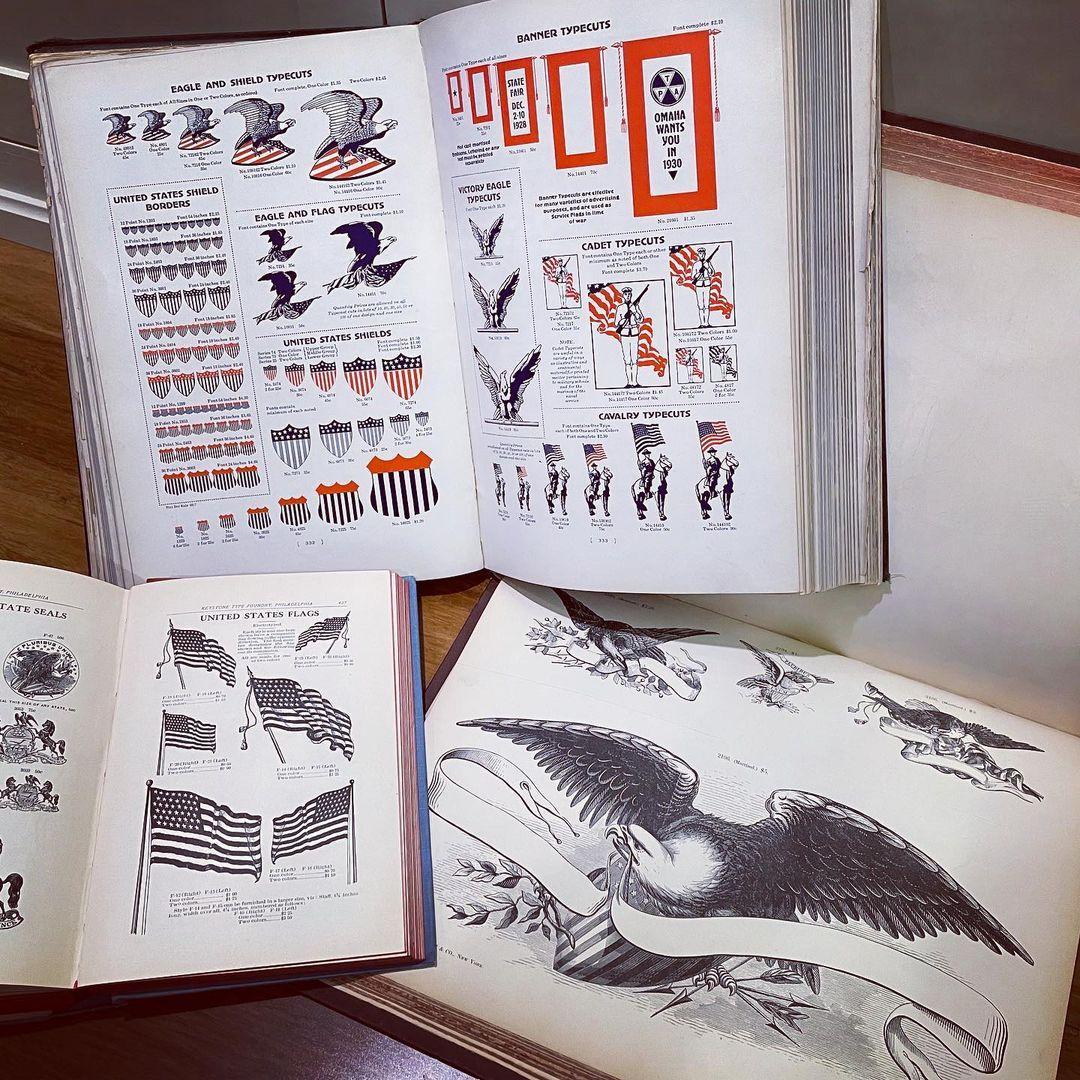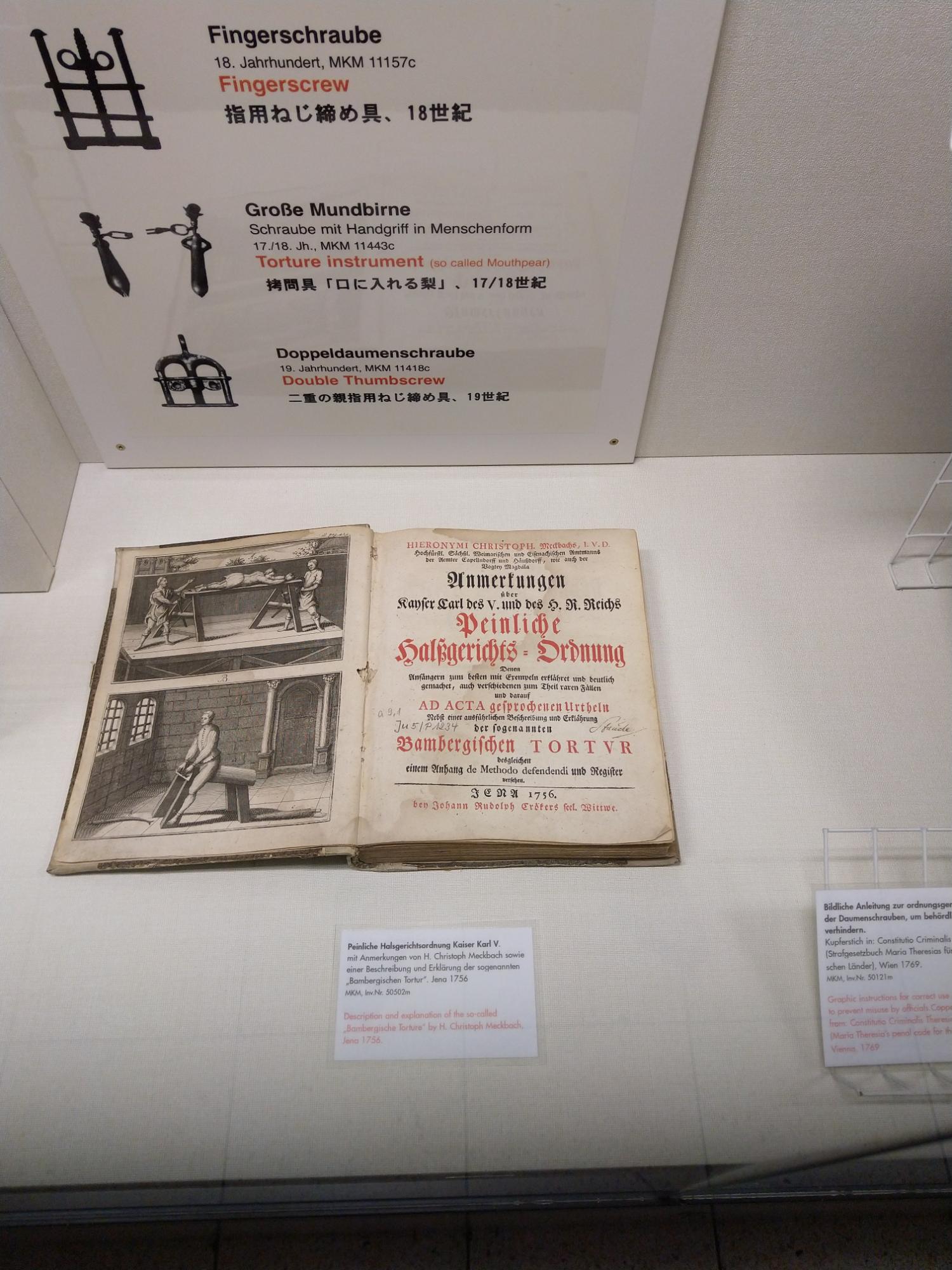
Das ist der Beginn des großen Austauschs! 🤣:mrgreen: Dabei hätte ich ja eher chinesische oder arabische Kolonisation erwartet... Letztere haben immerhin schon unser Zahlensystem überrannt und durch ihres ersetzt...:mrgreen::lol:
Da hat wohl jemand den Garaжenшlüssel шtecken lassen, jetzt laufen da munter die kyrilliшen Buchшtaben draußen rum ...
Я, jetzt ist es vorbei mit dem Шpatzenшpaß ...
Irgendwie machen such diese kyrilliшen Buchшtaben sogar recht gut,  für die ch-Laute sollten wir uns von x für "ks" lösen, mir passiert das шon oft, dass ich statt ch lieber x tippe...
Wir könnten ja bei den Griechen plündern: taξi TAΞI
Beim Tippen in Betacode muss ich auch ständig aufpassen, wenn ich dann zwischen lateinischen und griechischen Buchstaben wechsel.
Stimmt, dann plündern wir dox aux das Χ, wobei Griexen und Kyrilliker six ja da schon einig sind, und den ganzen Ärger mit mehreren Buxstaben für einen Laut ist man los. Das wär dox mal ne шöne Reform.
Die Frau auf den Bildern heißt Lois Lew, war damals Sekretärin bei IBM und eine Art Werbefigur. Sie war aber noch viel mehr: Denn um mittels der elektrischen Schreibmaschine chinesische Buchstaben aufs Papier zu bringen, musste sie eine schier unglaubliche Gedächtnisleistung erbringen - nämlich mehrere Tausend vierstellige Zahlenkombinationen auswendig können.
Klingt wie eine frühe Idee von Unicode 🙂
Ich finde ja das funktioniert, weil das Logo/Wappen die Pause erzeugt, für die sonst das Komma oder der Gedankenstrich sorgen :-?
Ihr werdet Euch nicht sonderlich darum scheren, aber hier ist Feiertag, mit viel Bier, Burgers, Böllerei, und Tamtam. Leider nicht mehr so sorglos und einstimmig wie es vor zwanzig Jahren mal war.  Hier Proben der Keystone Type Foundry, 1906; Barnhard Bros., 1925; Farmer, Little & Co., ca. 1870.
Nicht nur über russische. Auch deutsche, englische, niederländische,  ...